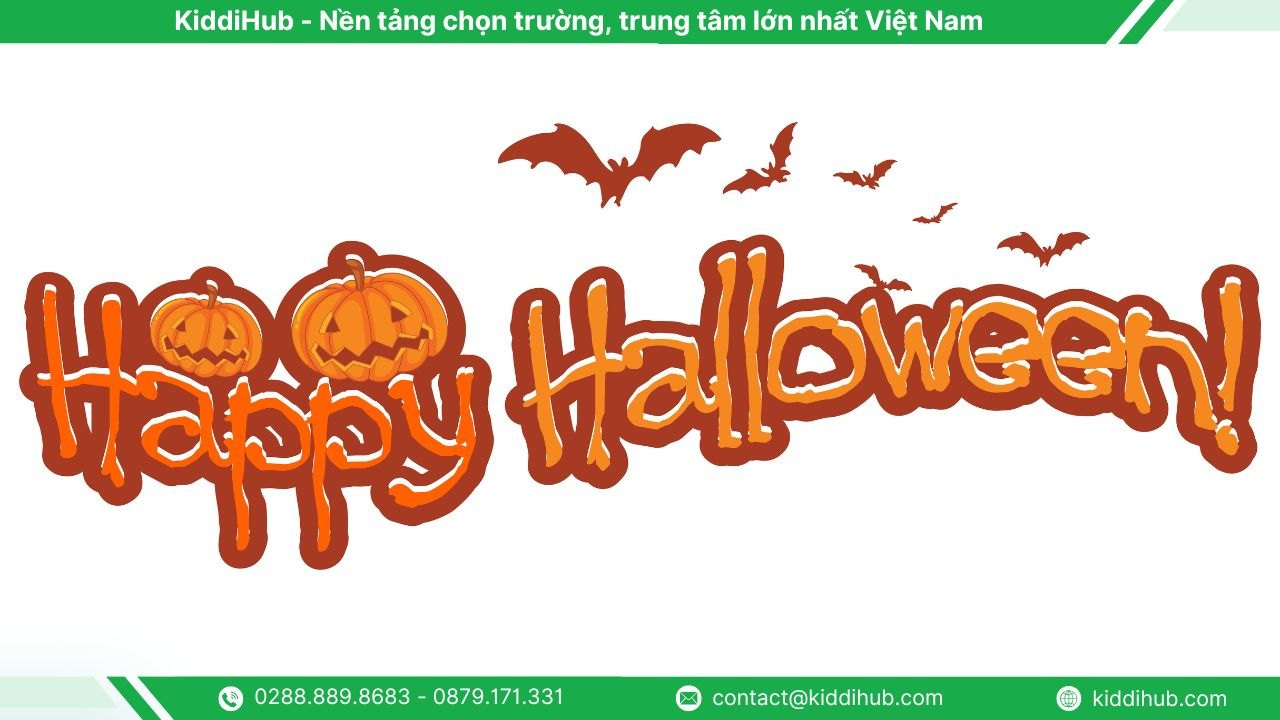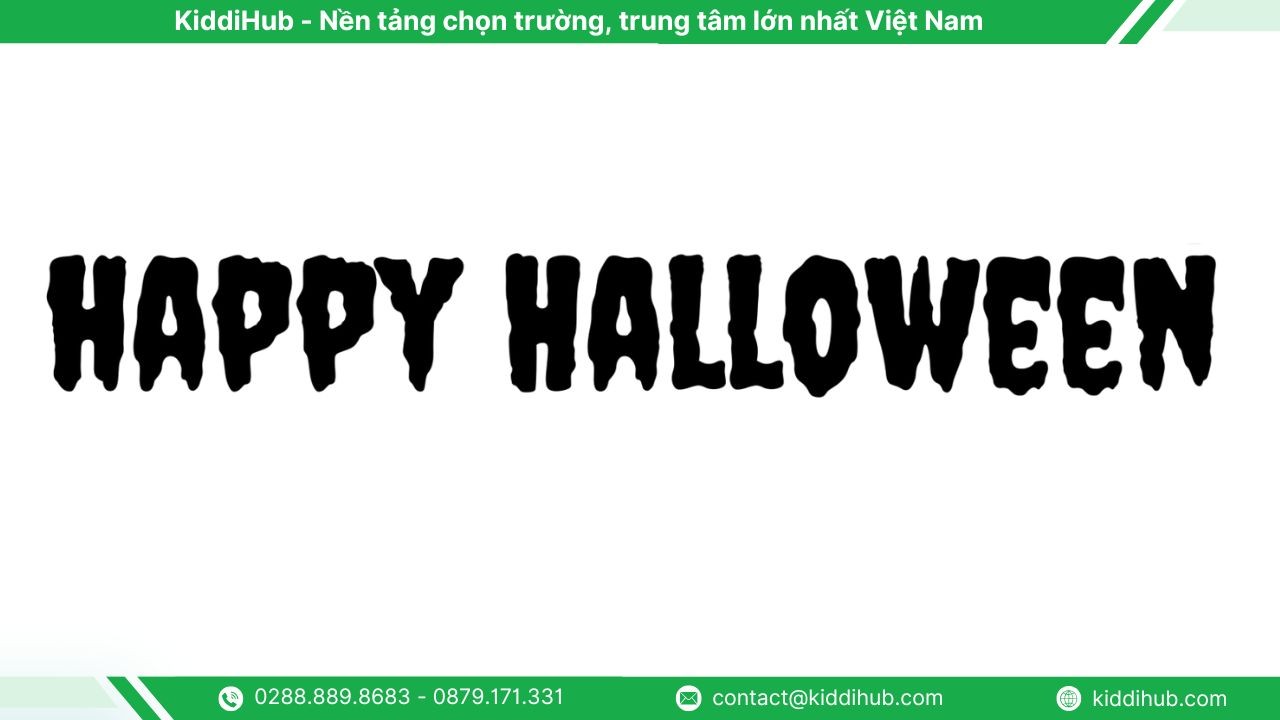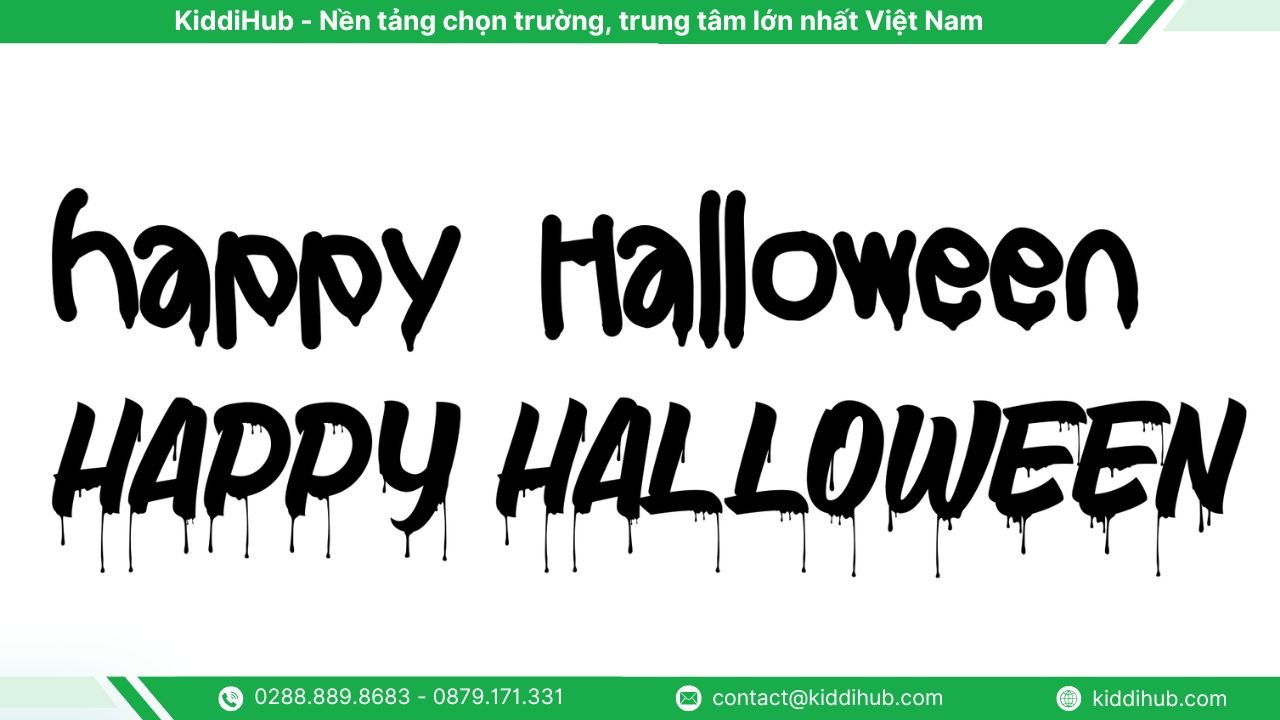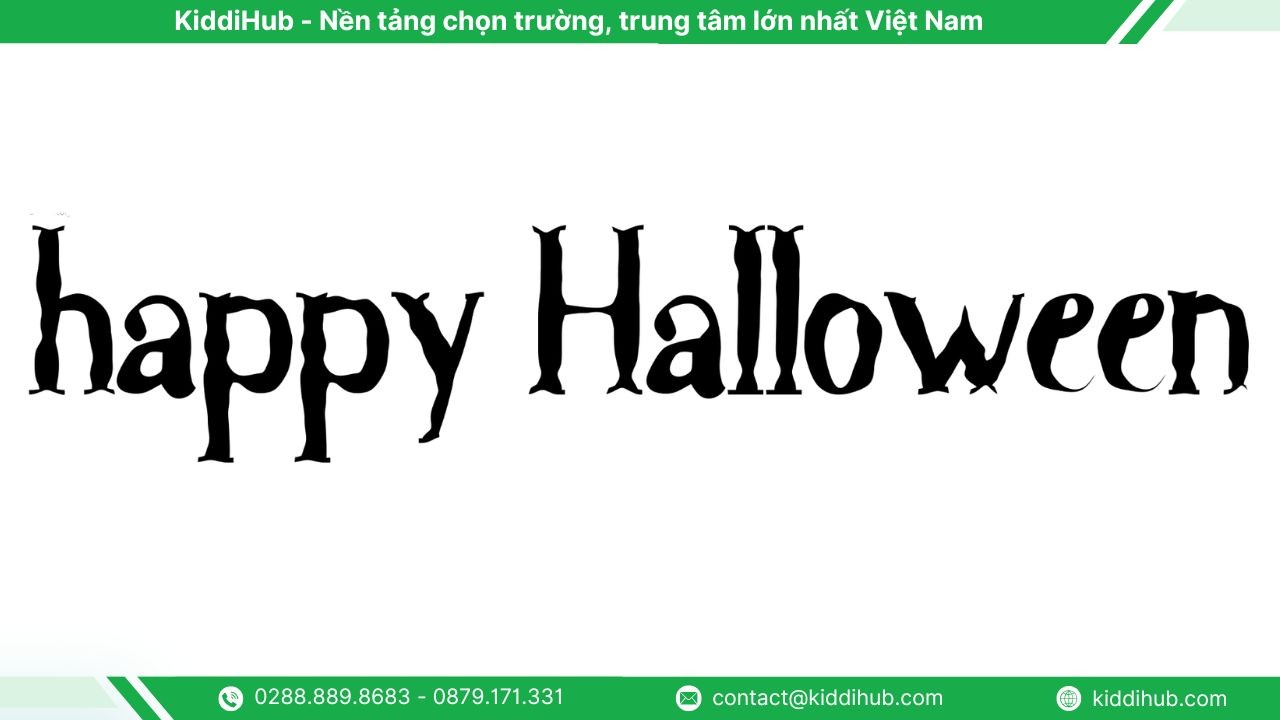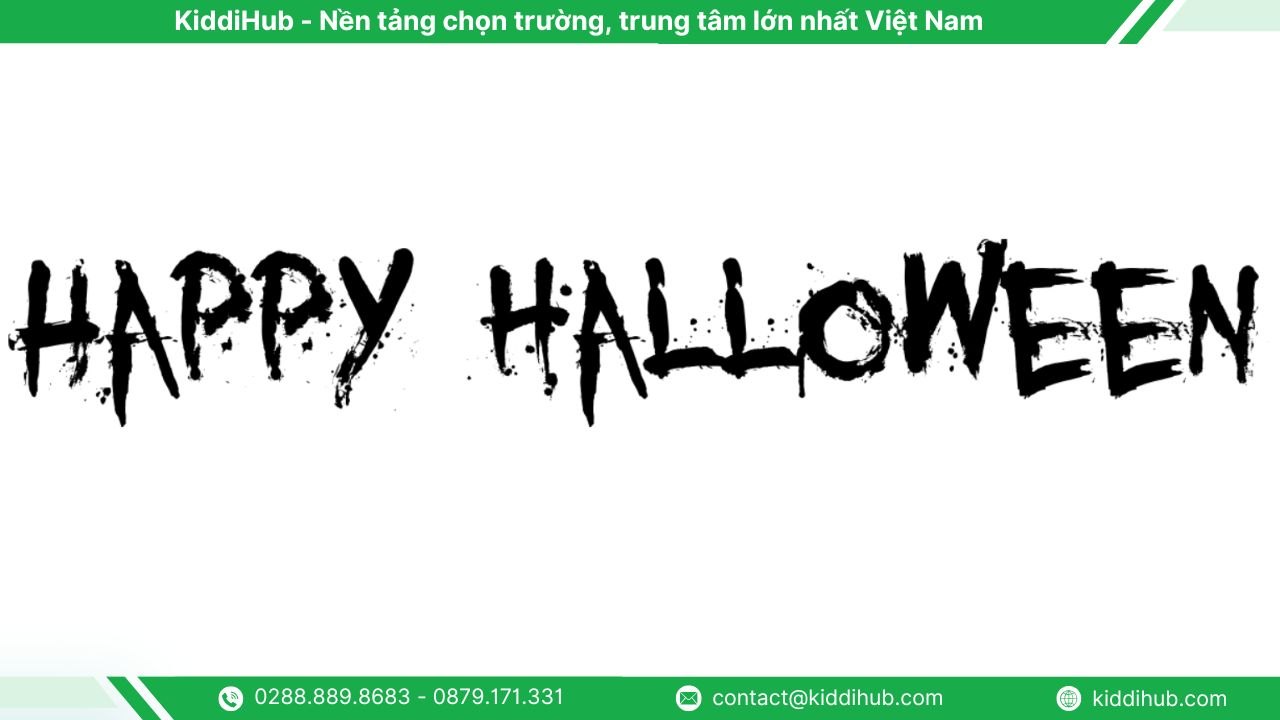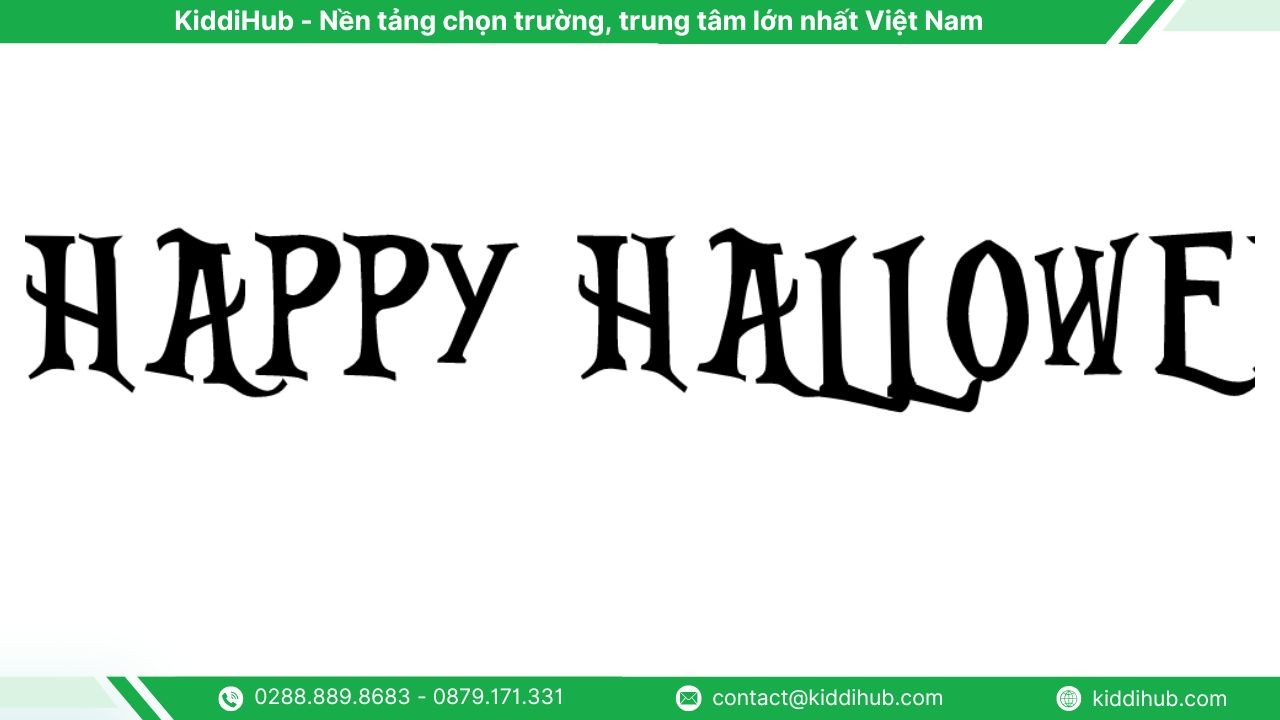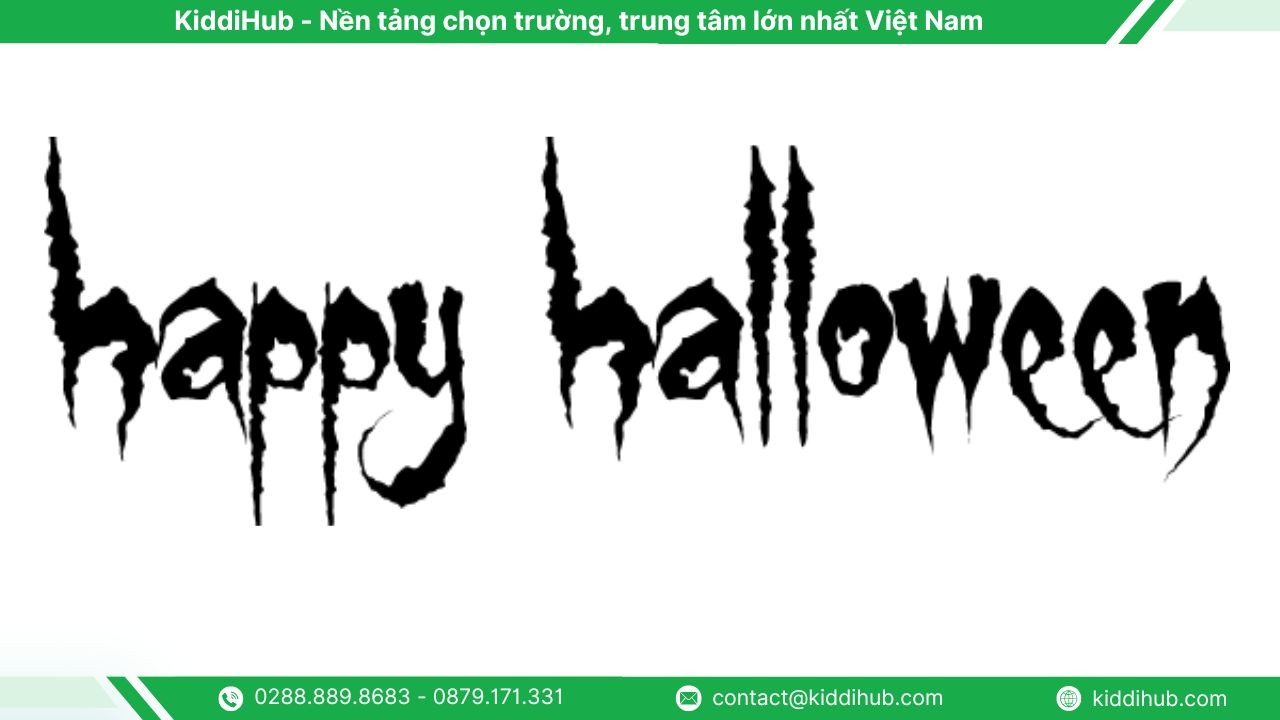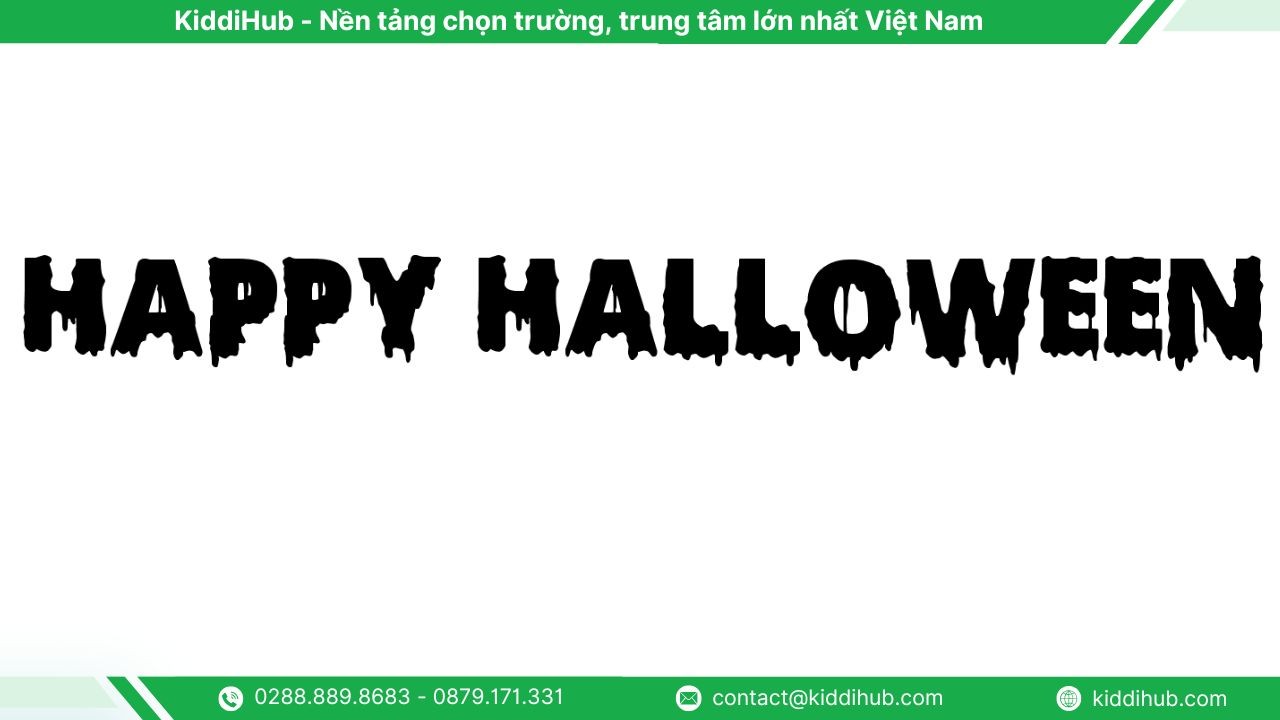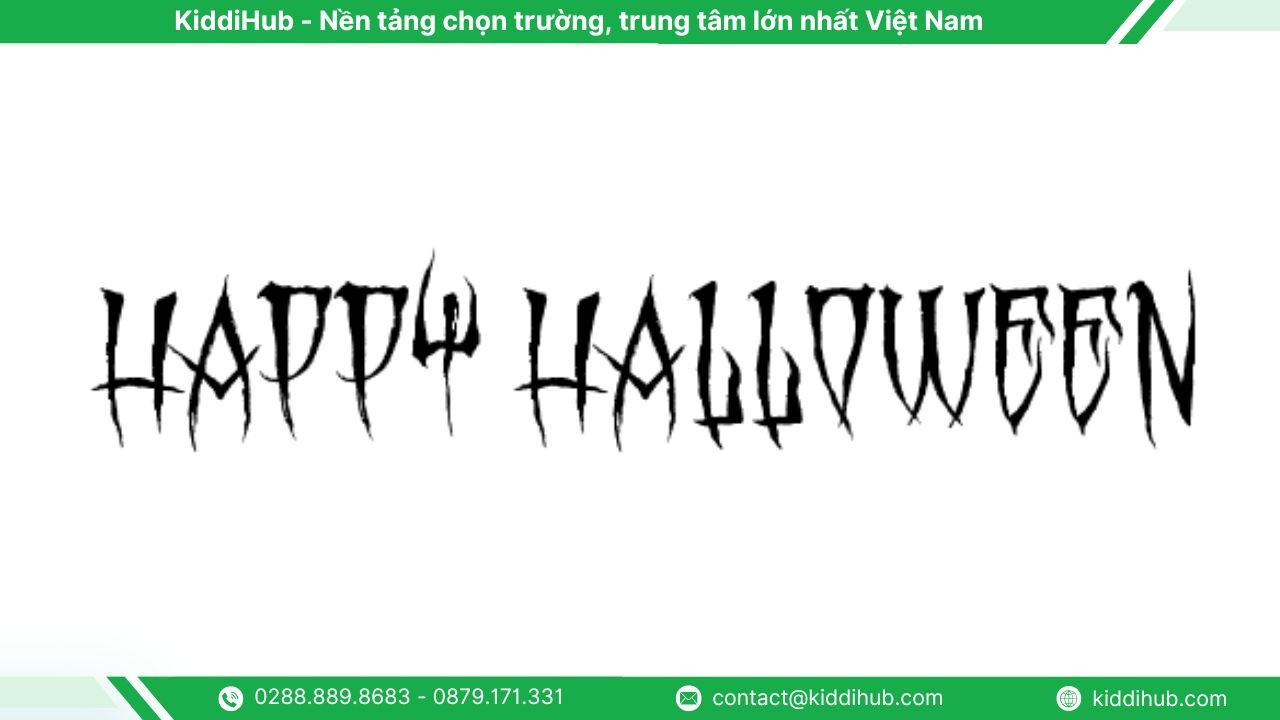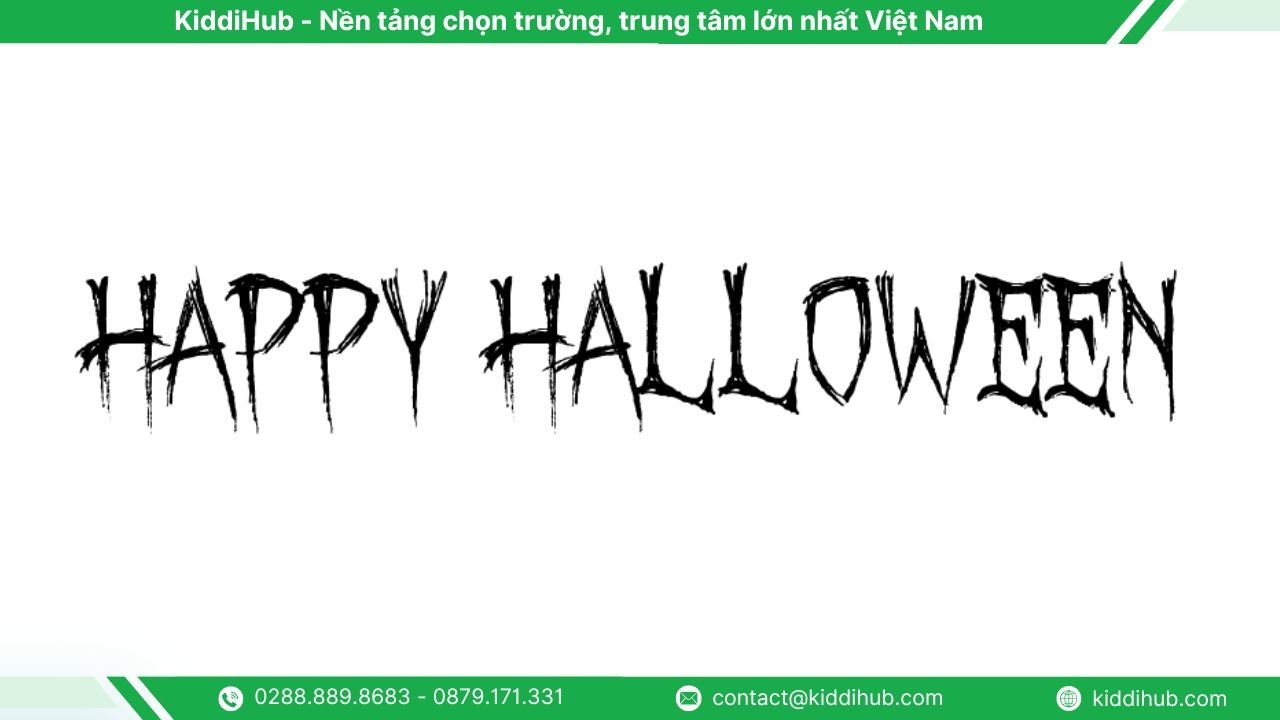
Mỗi khi tháng Mười đến, bầu không khí Halloween lại tràn ngập khắp nơi, từ cửa hàng trang trí, mạng xã hội đến những chiến dịch truyền thông lớn. Trong thế giới thiết kế, yếu tố giúp truyền tải tinh thần ma mị rõ ràng nhất chính là “font Halloween”. Đây không chỉ là kiểu chữ thông thường mà còn là phong cách thể hiện không khí của lễ hội đầy sắc cam, khói mù và ánh nến le lói trong đêm tối.
Font Halloween được các nhà thiết kế yêu thích vì chúng mang hơi thở của sự bí ẩn, kinh dị nhưng cũng có chút vui nhộn, phù hợp cho nhiều dạng nội dung. Một poster phim ma, một tấm thiệp mừng Halloween, hay video mở đầu cho buổi party đều cần đến những kiểu chữ đặc biệt này. Chính vì vậy, việc lựa chọn đúng font Halloween không chỉ giúp cho thiết kế nổi bật mà còn thể hiện được cảm xúc chủ đạo của dịp lễ.
Font Halloween có những đặc điểm nhận dạng riêng biệt giúp chúng khác hoàn toàn so với các loại font thông thường. Nét chữ của chúng thường có phần "quái dị" để gợi lên không khí rùng rợn kết hợp với những ảnh halloween kinh dị để tạo nên không khí của ngày 31 tháng 10 đặc trưng. Các đường nét có thể nhọn, gợn sóng, hoặc uốn cong như đang tan chảy. Một số kiểu font sử dụng hiệu ứng hình ảnh đi kèm, như giọt máu đỏ rơi xuống, màng nhện phủ quanh chữ hay chiếc bóng mờ lẩn khuất ở từng nét gạch.
Màu sắc chủ đạo khi phối với font Halloween thường xoay quanh gam màu cam, tím, đen và trắng. Mỗi màu mang ý nghĩa riêng: cam biểu trưng cho bí ngô, đen là đêm tối, tím là yếu tố huyền bí, còn trắng là màu của sương mù hoặc linh hồn.
Có thể chia font Halloween theo ba nhóm phong cách chính:
Font Creepster được xem là biểu tượng trong thế giới thiết kế Halloween. Với hiệu ứng chữ như đang rỉ máu, Creepster mang lại cảm giác vừa kinh dị vừa lôi cuốn, khiến người xem lập tức liên tưởng đến những cảnh tượng rùng rợn trong phim ma cổ điển. Mỗi ký tự đều có độ dày và sự méo mó vừa phải, giúp giữ tính dễ đọc mà vẫn toát lên vẻ ma mị đặc trưng.
Font này thường được sử dụng cho tiêu đề poster, bìa phim kinh dị hoặc banner quảng bá sự kiện Halloween ngoài trời. Khi kết hợp cùng tông màu đỏ, cam hoặc tím, Creepster tạo hiệu ứng thị giác mạnh mẽ. Bạn có thể tải font này miễn phí trên các trang như DaFont hoặc Fontspace.
Dripping Marker gây ấn tượng mạnh với hiệu ứng “chảy mực” đặc trưng, khiến cho từng ký tự trông như được viết bằng máu tươi. Điều này tạo cảm giác bất an, thích hợp cho các thiết kế muốn nhấn mạnh yếu tố rùng rợn. Dáng chữ to, đậm và có độ tương phản cao giúp font dễ nhìn ngay cả khi dùng cho tiêu đề cỡ lớn.
Font này phù hợp cho thiệp mời tiệc Halloween, tiêu đề video kinh dị hoặc poster phim trinh thám. Bạn có thể phối Dripping Marker cùng nền tối và hiệu ứng ánh sáng đỏ để làm nổi bật cảm giác ghê rợn. Nó thường được các nhà thiết kế yêu thích vì mang phong cách “classic horror” rất đặc trưng.
Pumpkin Story mang hơi hướng hoạt hình tươi vui, phù hợp cho các thiết kế Halloween hướng đến trẻ em hoặc gia đình. Nét chữ tròn đầy gợi cảm giác thân thiện, gần gũi như những quả bí ngô với nụ cười tinh nghịch trong đêm lễ hội. Mỗi ký tự đều được bo tròn khéo léo, tạo nên tổng thể sinh động và dễ thương.
Font đặc biệt thích hợp cho in ấn hoặc trang trí không gian lớp học, cửa hàng, quán cà phê. Khi kết hợp cùng màu cam và đen, Pumpkin Story giúp thiết kế trở nên hài hòa giữa nét ma mị và sự vui nhộn. Font này có sẵn miễn phí trên nhiều thư viện font phổ biến.
You Murderer BB tái hiện hình ảnh những dòng chữ viết vội bằng dao hoặc sơn trên tường, tạo cảm giác kinh hoàng và căng thẳng. Phong cách nguệch ngoạc nhưng có chủ ý khiến nó trở thành lựa chọn lý tưởng cho các thiết kế cần yếu tố “bụi bặm” và rợn người. Mỗi ký tự như mang theo câu chuyện đau thương ẩn giấu sau vết máu khô.
Font này cực kỳ thích hợp cho poster phim, truyện tranh ma hoặc các ấn phẩm truyền thông mang chủ đề tội ác. Khi phối với nền tường nứt hoặc texture kim loại rỉ sét, hiệu ứng của You Murderer BB sẽ phát huy tối đa. Font có thể tải tự do cho mục đích cá nhân.
Lấy cảm hứng từ bộ phim nổi tiếng cùng tên, font Nightmare Before Christmas pha trộn giữa nét cổ điển và hoạt hình kỳ quái. Những đường cong uốn lượn khiến chữ trông như đang chuyển động, phù hợp cho các thiết kế muốn gợi cảm giác phép thuật và kỳ ảo. Nó không quá đáng sợ, mà thiên về nét nghệ thuật đầy cá tính.
Font này được nhiều nhà thiết kế chọn cho thiệp mời, tiêu đề video và các ấn phẩm nghệ thuật mang âm hưởng lễ hội. Khi phối với màu trắng và tím, kiểu chữ này tạo ra không gian vừa huyền bí vừa ấm áp, hoàn hảo cho phong cách Halloween pha cổ tích.
Gypsy Curse là font mang hơi thở vintage xen lẫn yếu tố huyền bí. Những ký tự trong font có nét thon dài, như được viết bằng tay trên những cuốn sách phép cổ xưa. Nhờ vậy, font này tạo cảm giác cổ kính nhưng vẫn đầy cuốn hút. Người xem dễ dàng liên tưởng đến hình ảnh phù thủy, nến, và làn khói mờ ảo.